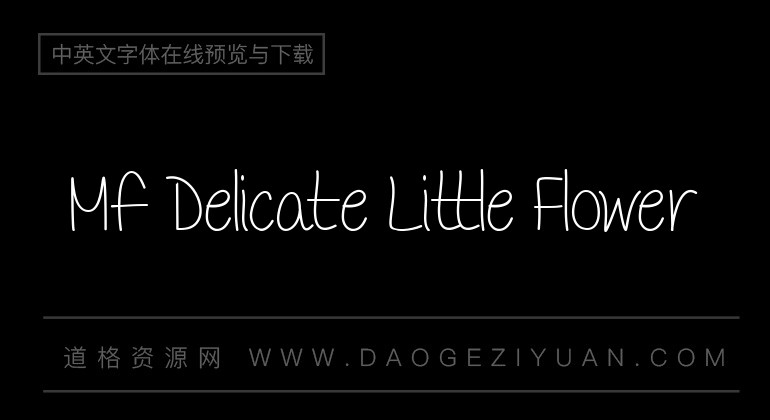
Mf Delicate Little Flower
Mf Delicate Little Flower 是一款精致的小型花卉字体,由著名的设计师Marianne Farley所设计。这款字体的特点是柔和的线条,每一笔都极具精致,且拥有一种清新的外观,极具可爱的感觉。它适合用于各种类型的设计,如海报、书籍、杂志、网页等,能够给视觉效果增添一份温柔而又精致的气息。
Mf Delicate Little Flower是一款非常不错的手写艺术字体,具有很好的视觉感,适合于文化类的宣传设计、商业类品牌的广告和产品包装设计以及个性化文字排版等较多场景。